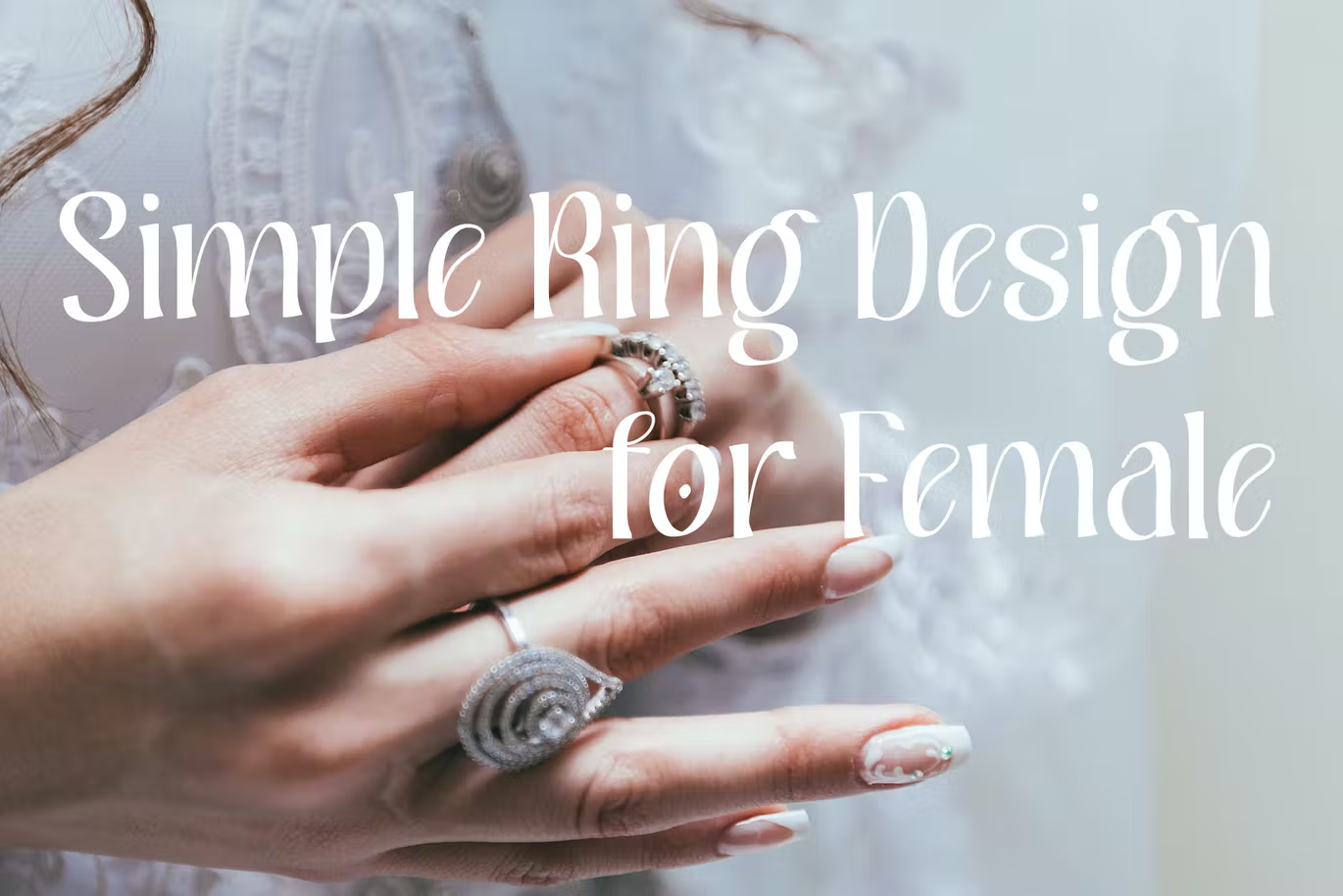
Hildor Beautiful Display Font
Description de Hildor Beautiful Display Font
Hildor est une belle police d’affichage
Hildor Beautiful Display Font un ensemble complet de lettres majuscules et minuscules, de symboles multilingues, de chiffres, de ponctuations et de ligatures. En outre, il comprend de courts swashes minuscules de début et de fin, des swashes minuscules de fin, qui servent à relier deux mots ou lettres (c’est si parfait pour les invitations, les monogrammes), de longs swashes minuscules de début et de fin de cœur.
La police a une texture lisse, elle serait donc parfaite pour tous les types de techniques d’impression + vous pouvez faire de la broderie, de la découpe au laser, de la feuille d’or, ce qui rend la police fabuleuse ! En outre, il existe de nombreuses alternatives stylistiques, ce qui rend chaque lettre différente.
Glyphes standards, lettres majuscules et minuscules, chiffres, large gamme de ponctuations et de ligatures.
Les lettres minuscules incluent des swashes de fin.